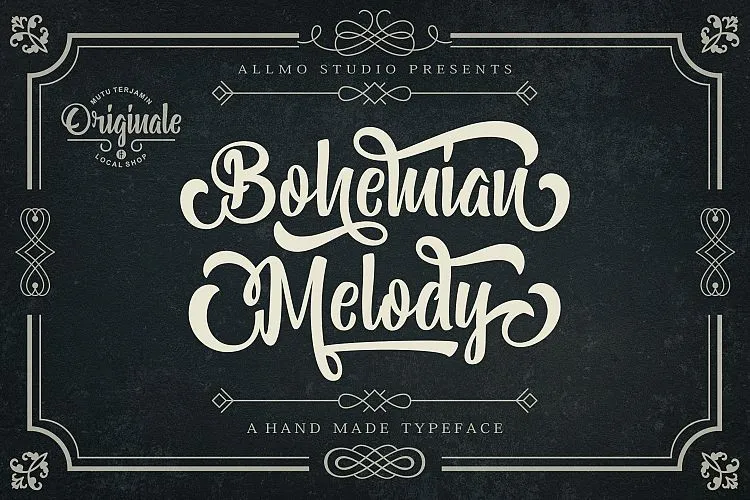
Bohemian Melody Font – Fonte Grátis
Bohemian Melody Font
Saudações amantes do design, aqui está uma descrição envolvente para a Bohemian Melody Font, uma Script Font que chega ao seu projeto com um toque irresistivelmente vintage e moderno. M.0Type nos apresenta Sugarly, uma tipografia de script com elementos típicos de estilos antigos, prontas para transformar seu trabalho em algo excepcional. A Bohemian Melody é mais do que apenas uma fonte; ela traz uma combinação singularmente poderosa e inovadora. Confortável e elegante ao mesmo tempo, essa fonte natural, moderna e vintage oferece um toque personalizado e autêntico às suas criações. Ela atende a todos os seus requisitos de identidade visual, seja para criar uma marca forte em cartões de visita ou para dar o tom certo à sua web página. Com Bohemian Melody na sua paleta de fontes, você pode certificar-se de que sua personalização é impecável e única. Esta fonte não só tornará seu trabalho mais profissional, mas também fará a diferença em como seus clientes o reconhecem e respeitam. Por isso, Bohemian Melody é uma ótima escolha para qualquer projeto onde você deseja que sua marca seja notada com eficácia e estilo. Essa fonte completa a paleta de M.0Type, oferecendo uma variedade de opções para qualquer designer que busque personalidade e originalidade em suas criações. Bohemian Melody é mais do que uma ferramenta de design; ela é um amigo fiel que adicionará valor imediatamente ao seu projeto, tornando-o ainda mais memorável e único.